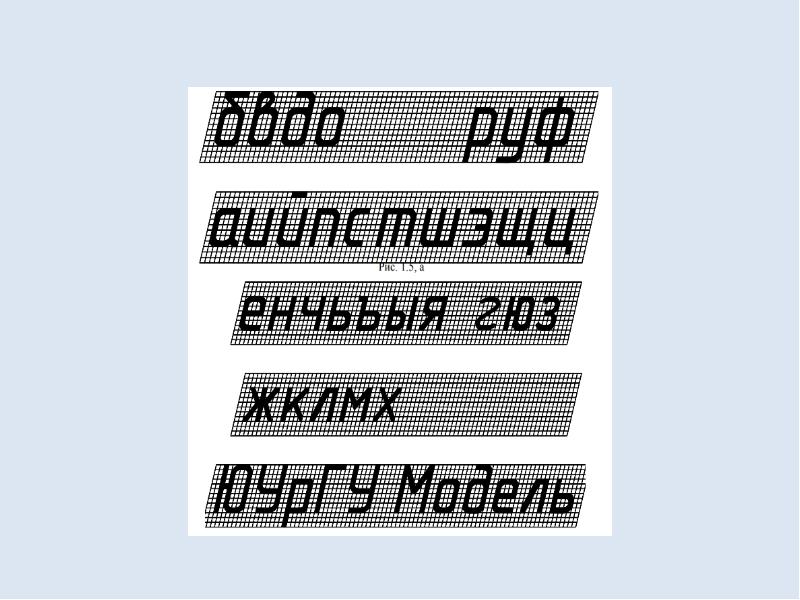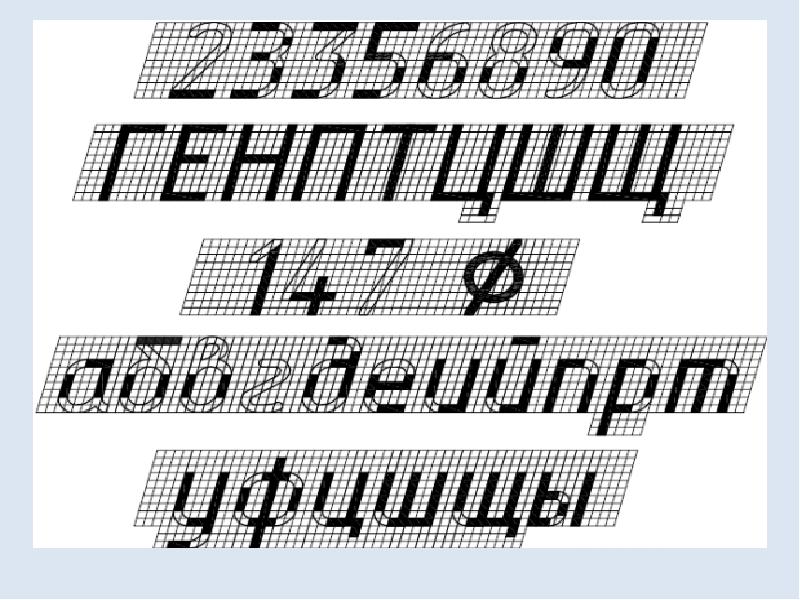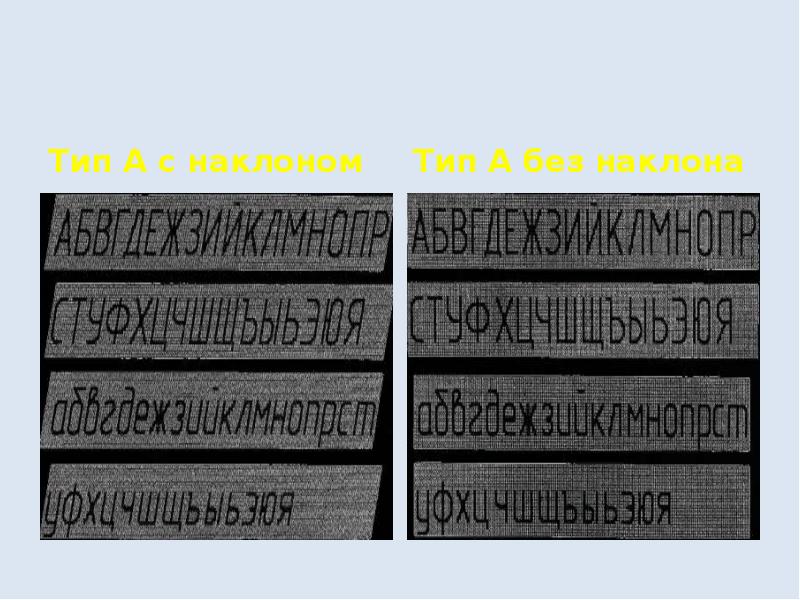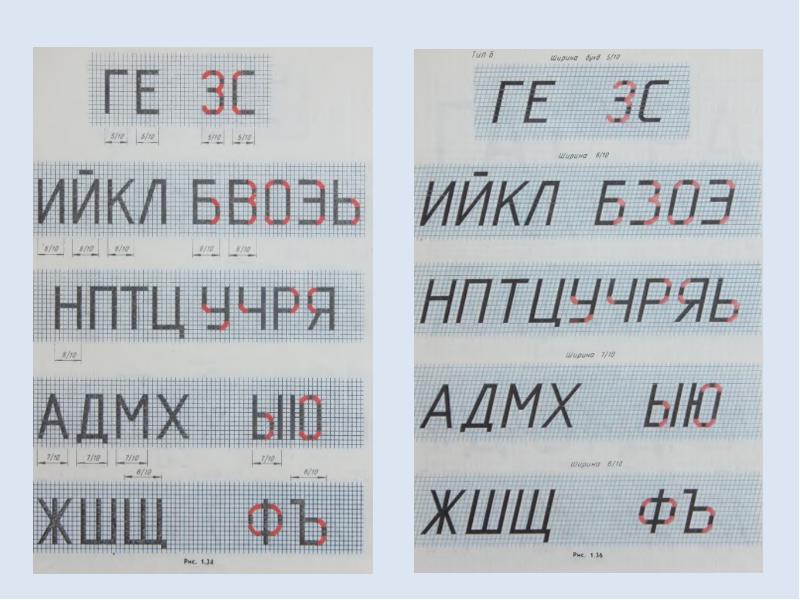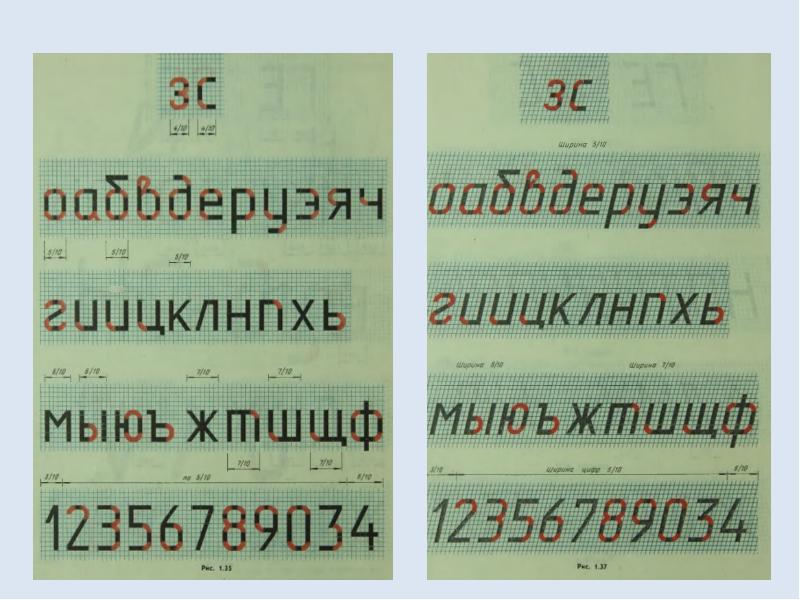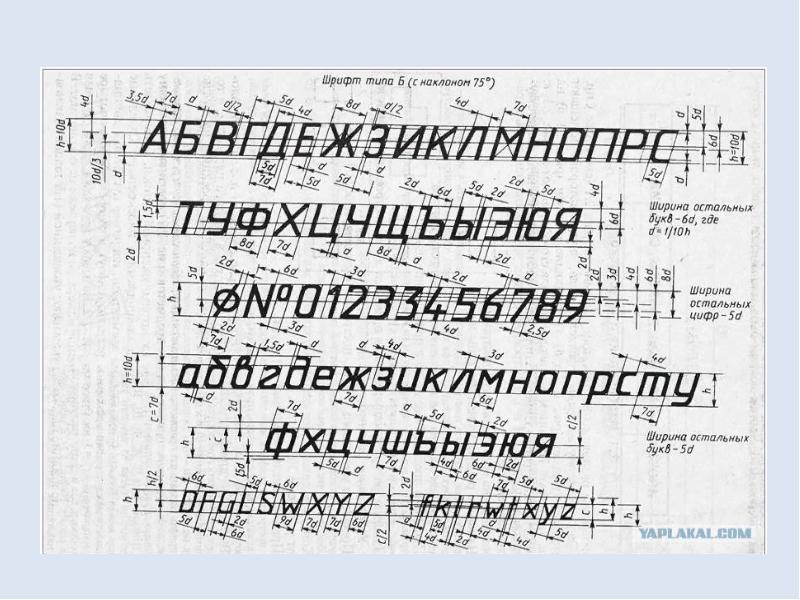
Шрифты чертежные
Тип А с наклоном
Тип А архитектурно - строительный
Рекомендуется использовать шрифт тип Б с наклоном 75 к основанию строки. Тип Б без наклона
Параметры шрифта
О с о б е н н о с т и к о н с т р у к ц и й б у к в , ц и ф р и з н а к о в П р о п и с н ы е б у к в ы Прописные буквы по их написанию можно...
О с о б е н н о с т и к о н с т р у к ц и й б у к в , ц и ф р и з н а к о в П р о п и с н ы е б у к в ы Прописные буквы по их написанию можно разделить на четыре группы. Буквы первой группы: Г, Н, П, Т, Ц, Е, Ш, Щ образованы прямолинейными элементами, расположенными горизонтально или под углом 75 к основанию строки.
Буквы второй группы: А, И, Й, Х, К, Ж, М, Л, Д также образованы прямолинейными элементами, Буквы второй группы: А, И, Й, Х, К, Ж, М, Л, Д также...
Буквы второй группы: А, И, Й, Х, К, Ж, М, Л, Д также образованы прямолинейными элементами, Буквы второй группы: А, И, Й, Х, К, Ж, М, Л, Д также образованы прямолинейными элементами, расположенными горизонтально или под углом 75 к основанию строки и наклонно или диагонально
Буквы третьей группы: Б, В, Р, У, Ч, Ъ, Ы, Я, С, Э образованы прямолинейными и криволинейными Буквы третьей группы: Б, В, Р, У, Ч, Ъ, Ы, Я, С, Э...
Буквы третьей группы: Б, В, Р, У, Ч, Ъ, Ы, Я, С, Э образованы прямолинейными и криволинейными Буквы третьей группы: Б, В, Р, У, Ч, Ъ, Ы, Я, С, Э образованы прямолинейными и криволинейными элементами. Буквы четвертой группы: О, З, Ю, Ф в основном состоят из криволинейных элементов.
Высота прописных букв – 10d. Ширина букв: Ж, Ф, Ъ, Ш, Щ, – 8d; ширина букв: А, Д, М, Х, Ы, Ю – 7d; остальных – 6d.
Ц и ф р ы По характеру начертания арабские цифры подразделяются на две группы: 1) цифры 1, 4, 7, состоящие только из прямолинейных элементов; 2)...
Ц и ф р ы По характеру начертания арабские цифры подразделяются на две группы: 1) цифры 1, 4, 7, состоящие только из прямолинейных элементов; 2) цифры 2, 3, 5, 6, 8, 9, 0, состоящие из сочетания прямолинейных и криволинейных элементов. Высота цифр равна высоте прописных букв – 10d. Ширина всех (кроме цифр 1 и 4): – 5d; ширина цифры 4 – 6d; цифры 1 – 3d.
С т р о ч н ы е б у к в ы Из всего алфавита только 15 строчных букв по конструкции отличаются от соответствующих прописных. В основе начертания этих...
С т р о ч н ы е б у к в ы Из всего алфавита только 15 строчных букв по конструкции отличаются от соответствующих прописных. В основе начертания этих букв лежит конструкция элементов буквы О. Высота строчных букв – 7d. При построении шрифта по вспомогательной сетке следует учитывать разную ширину букв. Буквы: ж, т, ф, ш, щ – 7d;. буквы: м, ю, ы – 6d.– остальные – 5d. Необходимо помнить, что расстояние между некоторыми буквами, например, Г и А, Г и Л уменьшается с 2d до размера, равного толщине линии букв. Минимальное расстояние между буквами в словах– 2d. Минимальное расстояние между словами – 6d. Минимальное расстояние между строчками текста – 17d.
Графическая работа
Параметры шрифта Размер соответствует номеру шрифта h и определяется высотой прописных букв в мм. ГОСТ допускает следующие размеры (высоту прописных...
Параметры шрифта Размер соответствует номеру шрифта h и определяется высотой прописных букв в мм. ГОСТ допускает следующие размеры (высоту прописных букв) шрифта: h = 1,8, 2,5; 3,5; 5; 7; 10; 14; 20; 28; 40